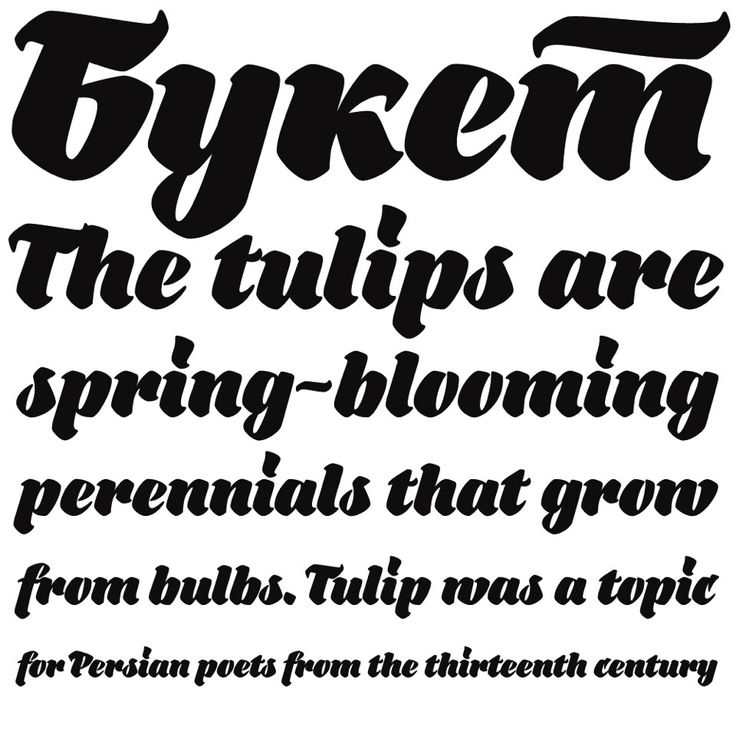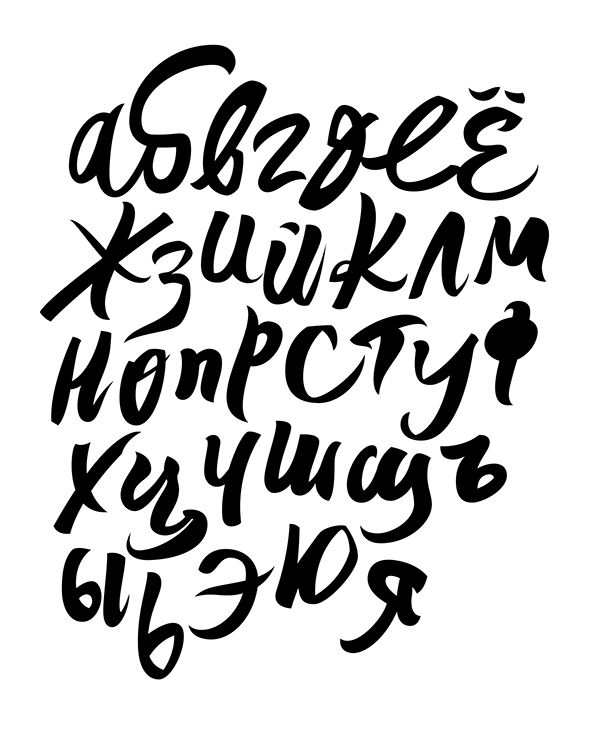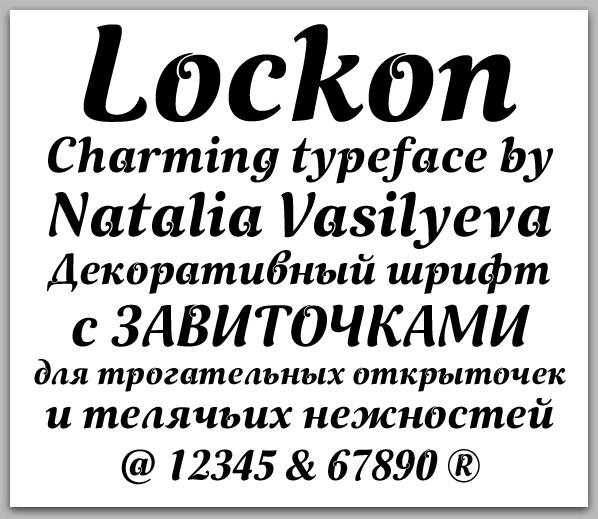
Красивый кириллический шрифт: 42+ лучших кириллических шрифта бесплатно (обновлено в 2021)
10 отличных шрифтов для русскоязычных проектов
В интернете можно найти десятки подборок отличных шрифтов, правда есть одно но: все они — латинские. Сегодня мы постараемся исправить это недоразумение.
Мы живем в эпоху изобретений и находимся на пике развития человечества. Люди уже летают в космос, путешествуют в ранее недоступные точки земли, а домашние хлопоты взяли на себя разнообразные гаджеты. Самое сложное сейчас − представить себе что-то совершенно новое, потому что все о чем бы вы не подумали, оказывается, уже кто-то придумал и создал минуту назад.
В этих реалиях художники и дизайнеры постоянно экспериментируют с объектами и инструментами вокруг себя.
Шрифт может сказать о продукте то, о чём не говорит его название — например, о его эксклюзивности, качестве или свежем взгляде создателя. И сегодня, команда Шуба Lab, поделится с вами 10 невероятно полезными шрифтами, которые вы сможете использовать в своих проектах для превосходного результата в будущем!
Отличный шрифт, который включает в себя 12 начертаний, множество различных лигатур и специальных символов. Единственный его минус заключается в том, что он платный (цена за весь комплект составит $595).
Это бесплатный гротескный шрифт. Он включает в себя 4 начертания: Light, Thin, Book, Regular. Шрифт с каждым днём набирает всё большую популярность и сейчас его можно назвать гельветикой (Helvetica) среди бесплатных шрифтов.
Это шрифт с засечками основан на Adobe Utopia и распространяется по свободной лицензии.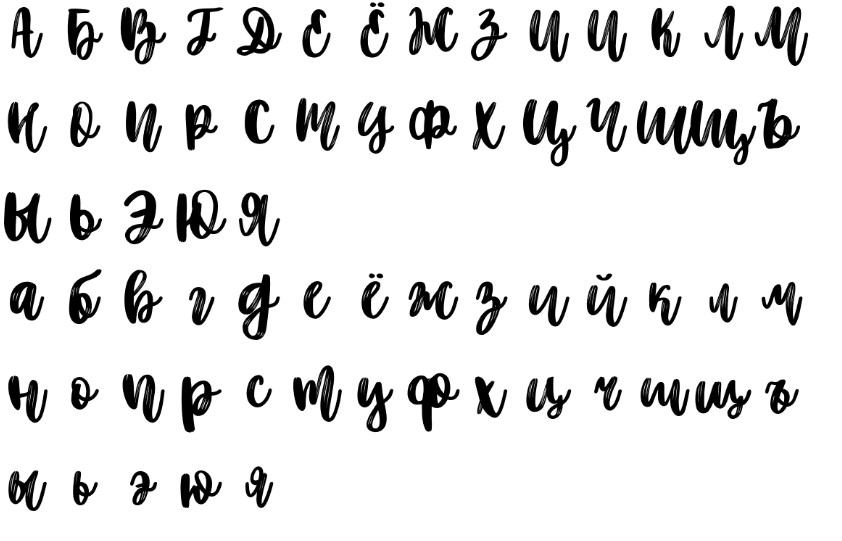
Кириллический акцидентный шрифт, который авторы решили распространять абсолютно бесплатно. Шрифт был создан в 2008 году и с тех пор находится в свободном доступе. Шрифт включает в себя 1 начертание и особенно пригодится для дизайнеров печатной.
Бесплатный, гротеск. И он достаточно «молодой»: разработан был в 2012 году. В наборе всего 2 начертания, но в то же время шрифт бесплатный. Так что не смотрите дареному коню в зубы, а поскорее добавляйте в свою коллекцию.
Акцидентный шрифт с засечками. Лишь одно начертание — но его будет достаточно для заголовка вашего журнала или первого экрана продающей страницы. Шрифт бесплатный и распространяется по стандартной лицензии.
Платный шрифт. Но два начертания вы можете скачать бесплатно и они отлично подойдут для оформления постеров, журналов и продающих страниц. Но за весь набор придется заплатить $279. Этот шрифт стоит своих денег, мы в этом убедились.
Акцидентный шрифт, который идеально подходит для дизайна логотипов, так или иначе связанных с кулинарией и гастрономией. Шрифт платный (49$) и в наборе всего одно начертание.
Огромное семейство шрифтов, включающее в себя 72 (!) начертания. В наборе можно найти шрифт для абсолютно любых целей. На данный момент шрифт продается со скидкой 90%! И сейчас все семейство Clio можно купить всего за $39.
Один из самых популярных платных гротесков в мире, а основан он был на известном шрифте Museo. Полный набор включает в себя 10 начертаний и приобрести себе его можно за 89$.
Шрифты, которые мы сегодня описали, станут хорошим подспорьем в создании дизайна ваших русскоязычных проектов. Здесь вы найдете все шрифты, которые вам могут понадобиться в ближайшее время. А когда на рынке появятся новые образцы кириллических шрифтов, мы обязательно расскажем вам о них.
50 самых популярных бесплатных кириллических шрифтов 2015 года
Из всех опубликованных шрифтов мы выбрали самые скачиваемые и составили из них подборку 50 самых популярных бесплатных кириллических шрифтов 2015 года.
Рядом с каждым шрифтом написано количество скачиваний, а ниже дана ссылка на скачивание шрифта.
1. Muller: 3142
2. Quinta Pro: 2993
3. Nexa Script: 2595
4. Gagalin: 2422
5. Frenchpress: 2356
6. Stampbor Grunge: 2307
7. Novito Nova: 2163
8. AC Boucle: 2130
9. Dewberry: 2118
Jasminum
Jasminum — каллиграфический свободный рукописный шрифт, названный в честь автора. Шрифт идеально подходит для придания индивидуальности вашим дизайнерским проектам.
Дизайн: Ясмина Зорник
Neoplanta BG
Neoplanta BG — современный шрифт с засечками для сербской кириллицы. Шрифт бывает Regular, Regular Italic, Bold, Bold Italic.
Дизайн: Stjepan Fileki
Nioki BG
Nioki BG — это современное семейство шрифтов без засечек для сербской кириллицы.